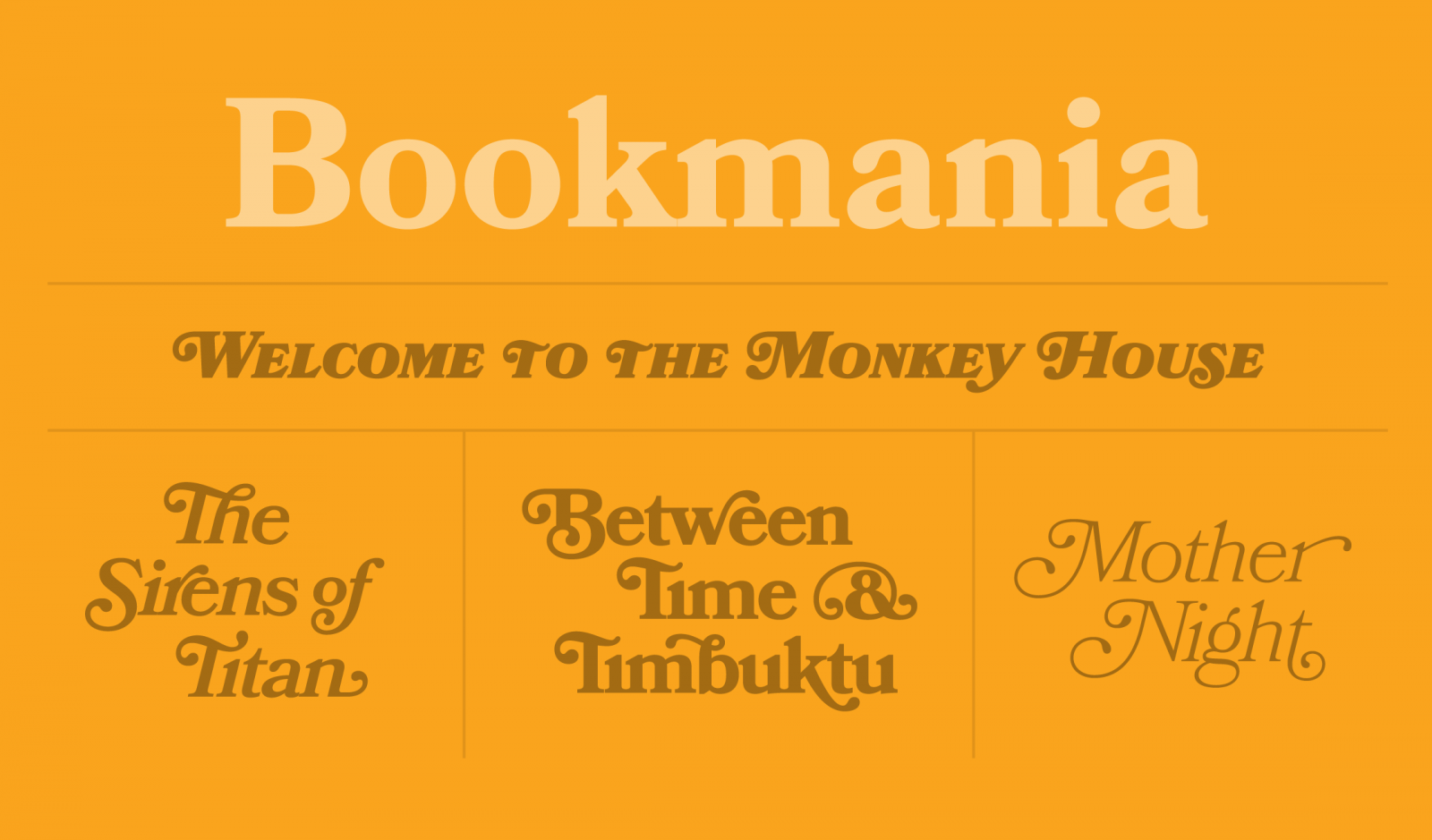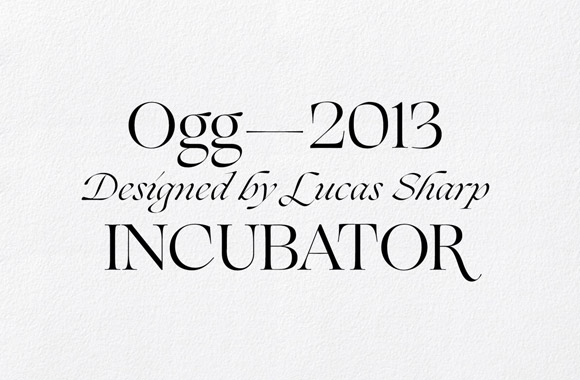
Với xu hướng thiết kế năm 2024, việc lựa chọn phông chữ không chỉ đơn giản là một quá trình chọn lựa mà còn là một cơ hội để thể hiện sự sáng tạo và cá nhân hóa. Trong bối cảnh đó, không thể không nhắc đến những fonts chữ hứa hẹn sẽ được sử dụng nhiều trong năm này. Từ những kiểu chữ cổ điển mang đậm vẻ đẹp truyền thống đến những lựa chọn hiện đại phản ánh sự tiến bộ của công nghệ, danh sách này không chỉ đem lại sự đa dạng mà còn khám phá những xu hướng mới trong ngành thiết kế. Hãy cùng khám phá và tìm hiểu về những font chữ này để tạo ra những thiết kế độc đáo và ấn tượng trong năm 2024.
Dưới đây là danh sách 10 phông chữ phổ biến mà gần đây nhiều nhà thiết kế đã chú ý đến. Một số trong số này là hoàn toàn mới, trong khi một số khác là các sản phẩm cũ nhưng đã được yêu thích và tái hiện lại một cách mới mẻ. Tất cả đều xứng đáng để thử nghiệm và có thể có một số trong số chúng sẽ là lựa chọn lý tưởng để làm cho danh mục thiết kế đồ họa của bạn trở nên sống động hơn trong năm 2024.
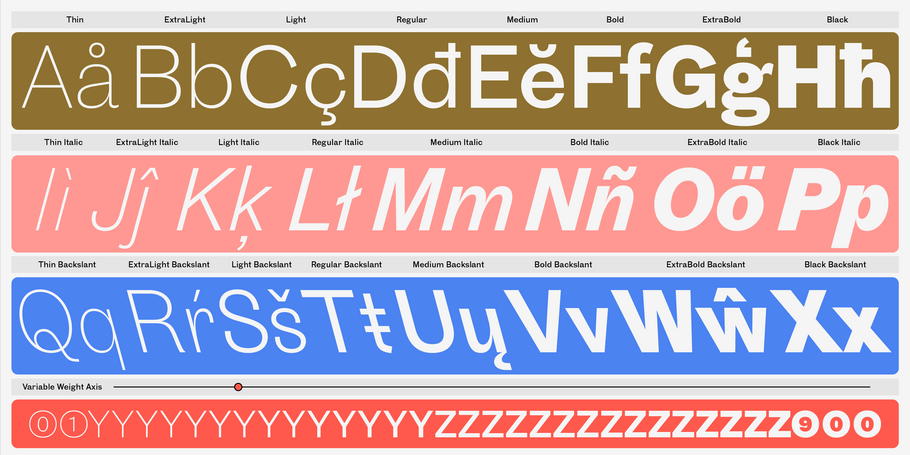
Touvló, sáng tạo từ Emilios Theofanous của Monotype Studio, mang ý nghĩa 'gạch' trong tiếng Hy Lạp, là sự kết hợp tinh tế giữa tinh thần kiểu chữ kỳ quặc của thời kỳ đầu của Anh và sức sống động, cá tính đặc trưng của riêng nó. Với tổng cộng 24 biến thể theo ba kiểu trên ba phông chữ khác nhau, cách diễn giải hiện đại và hấp dẫn về thể loại cổ điển này đủ linh hoạt để phù hợp với các bố cục kiểu chữ phức tạp nhất hoặc những thiết lập đặc biệt và bất ngờ.
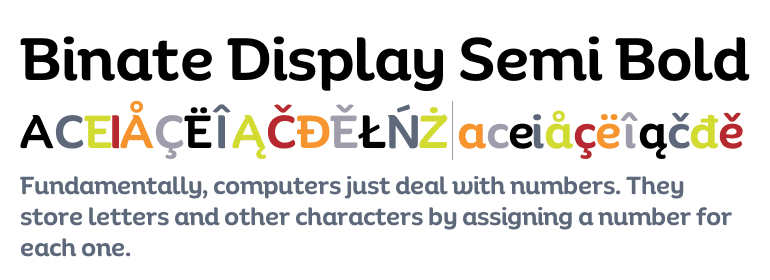
Binate kết hợp các đặc tính của sans-serif đặc trưng với phong cách hiển thị được lấy cảm hứng từ bút vẽ trang nhã. Đường nét của nó sắc nét và cứng nhắc, đồng thời, việc thử nghiệm một số móc dưới của Binate có thể giúp thiết kế trở nên dễ gần và thân thiện hơn. Phạm vi trọng lượng ấn tượng của nó khiến nó phù hợp với mọi thứ, từ những chi tiết nhỏ trên bao bì đến các kích thước lớn như biển quảng cáo và áp phích.
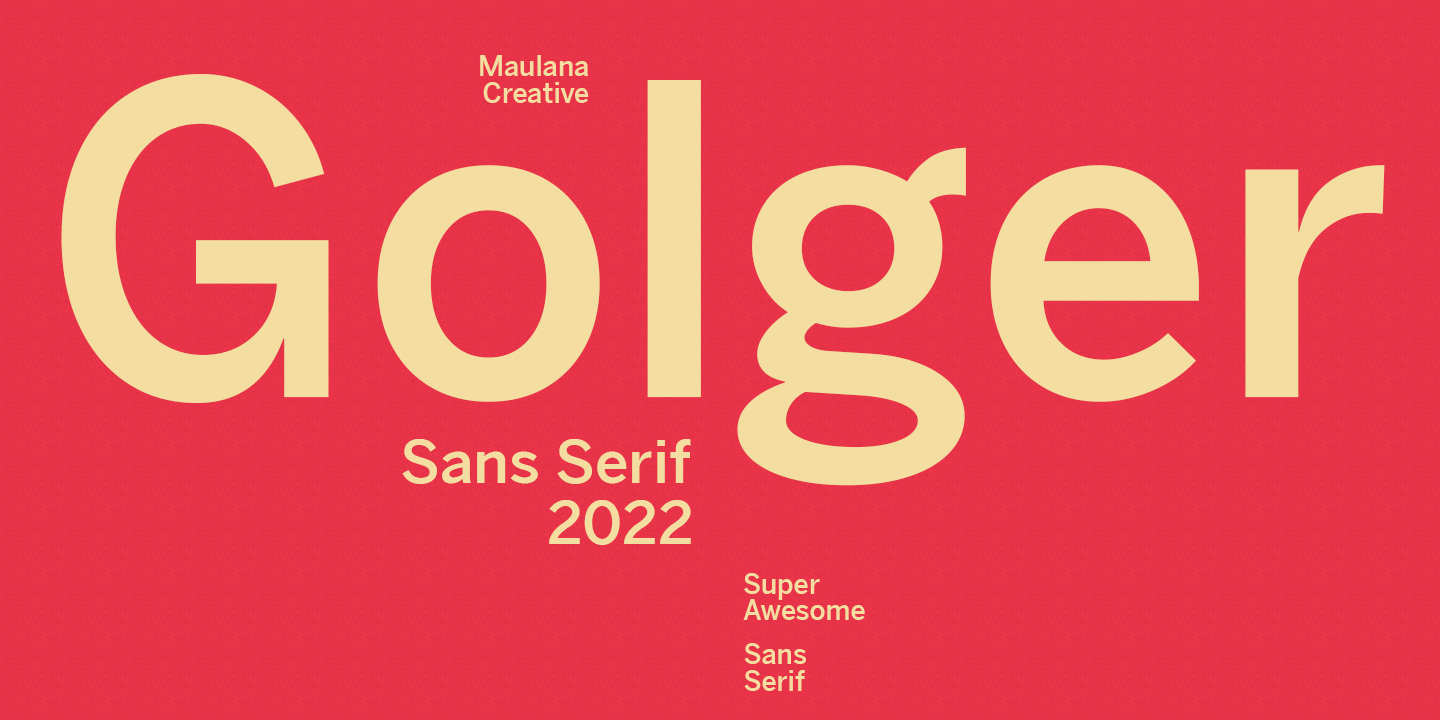
Golger Sans là một kiểu chữ sans-serif đương đại cổ điển, với nét đậm đậm và tính cách vui nhộn, nhất là từ những chữ ghép rải rác. Được thiết kế bởi Gilang Maulana, phông chữ này hỗ trợ hơn 100 ngôn ngữ ấn tượng, là một lựa chọn tốt cho thiết kế logo, phương tiện truyền thông xã hội, tiêu đề phim, sách, văn bản ngắn và dài cũng như để kết hợp với phông chữ chữ viết.
Ogg là một siêu họ serif thư pháp được thiết kế bởi Lucas Sharp, lấy cảm hứng từ chữ viết của nhà thư pháp thế kỷ 20 Oscar Ogg. Nó ghi lại sự kết hợp độc đáo giữa hình thức thư pháp và kiểu chữ thông qua việc sử dụng ngòi bút, bút vẽ và màu trắng được chạm khắc bằng tay, với năm trọng lượng và tổng cộng 10 phông chữ.
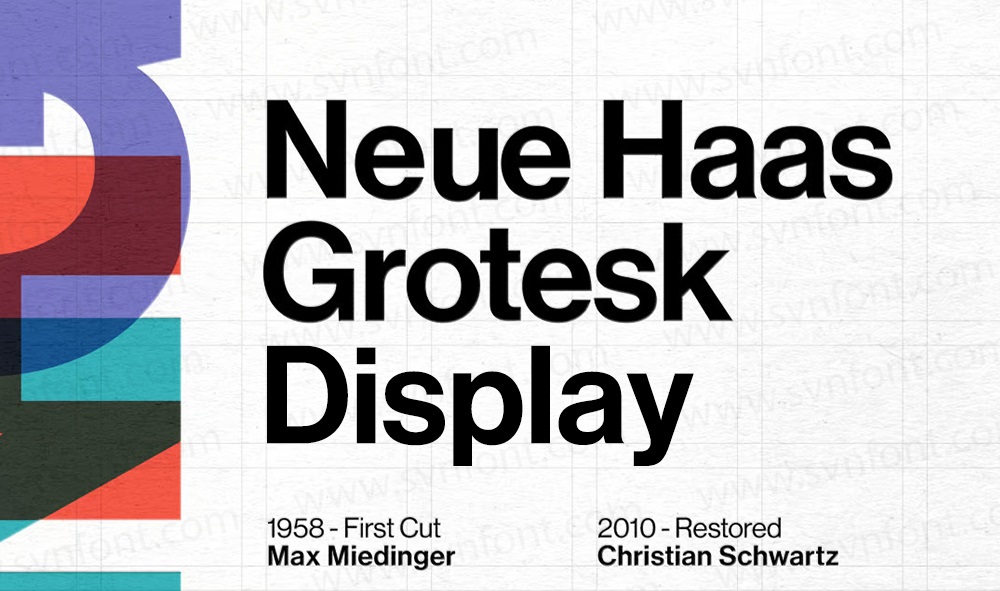
Neue Haas Grotesk, được thiết kế bởi Christian Schwartz, là một sự hồi sinh kỹ thuật số của Helvetica với tám độ đậm nhạt hiển thị và ba độ đậm đặc nữa, là một phông chữ linh hoạt cho thế giới hiện đại nhưng vẫn đảm bảo sự rõ ràng và dễ đọc của phông chữ gốc.
Garnett là một kiểu chữ sans serif đương đại, cứng cáp được thiết kế bởi Connor Davenport, kết hợp một chút ảnh hưởng của Gothic Mỹ, có sẵn sáu loại có trọng lượng in nghiêng phù hợp.
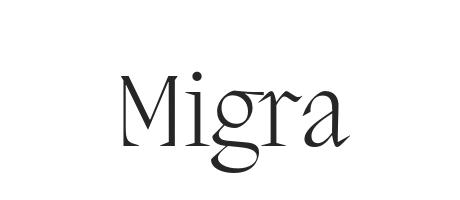
Migra là một phông chữ serif lấy cảm hứng từ những loài chim di cư, với tỷ lệ cô đọng, nét serif sắc nét và mảnh mai, được tạo bởi Valerio Monopoli với 8 độ dày và 16 kiểu.
Bookmania là sự hồi sinh kỹ thuật số mới mẻ của các kiểu chữ Bookman của thế kỷ 20, với 680 ký tự phong phú, được thiết kế bởi Mark Simonson.
Portrait là một phông chữ serif được thiết kế bởi Berton Hasebe, mô tả tối giản các kiểu chữ thời Phục hưng của Pháp, với bốn phân nhóm riêng biệt và nhiều tông màu.
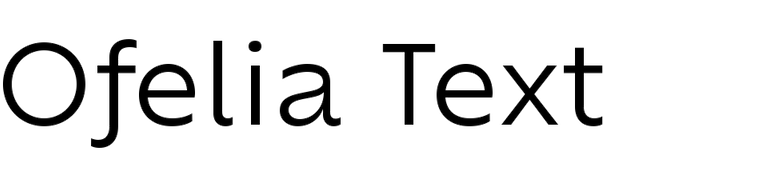
Ofelia là một phông chữ sans-serif hình học đa năng có hai kích thước quang học, được thiết kế để hoạt động tốt trong mọi tình huống, có sẵn với 10 mức độ đậm nhạt và các biến thể.
Bạn đã có trong tay 10 kiểu chữ tuyệt vời để áp dụng vào công việc thiết kế của mình trong năm 2024. Tuy nhiên, không ngừng khám phá là chìa khóa để trở thành một nhà thiết kế đỉnh cao. Vẫn còn vô số phông chữ hấp dẫn khác mà bạn có thể khám phá.